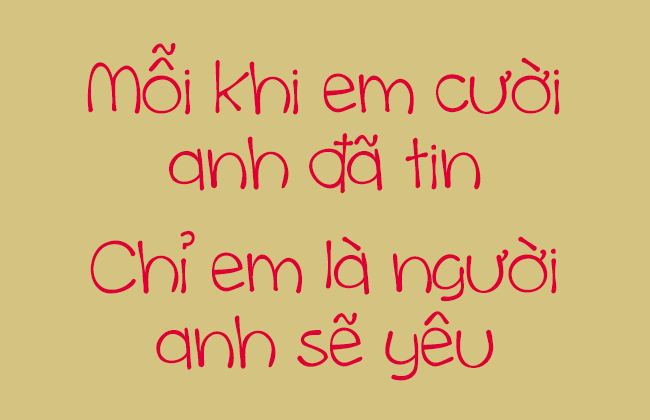
Cinnamoncake – một font viết tay cực kỳ đáng yêu. Font thích hợp cho các thiết kế về trẻ em, bánh kẹo, thiệp Giáng sinh,…
Nhà thiết kế: Brittney Murphy